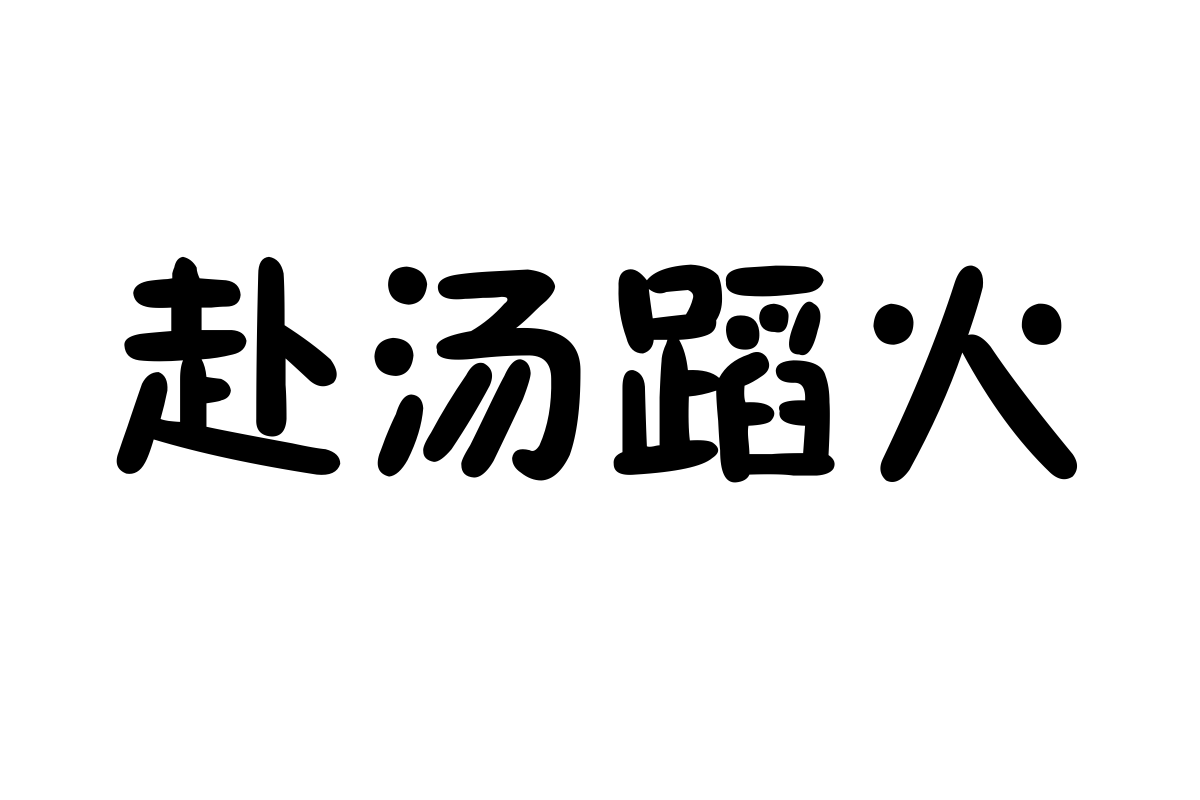
迷你简少儿字体是一款专为儿童设计的字体,具有以下特点:
1. 简洁明了:字体设计简洁,线条流畅,易于阅读和理解。
2. 可爱风格:字体采用卡通化的设计,色彩鲜艳,充满童趣。
3. 易识别:字体结构清晰,笔画简单,便于儿童学习和记忆。
4. 适合儿童:字体适用于儿童读物、儿童游戏等场景,能够吸引儿童的注意力。
迷你简少儿